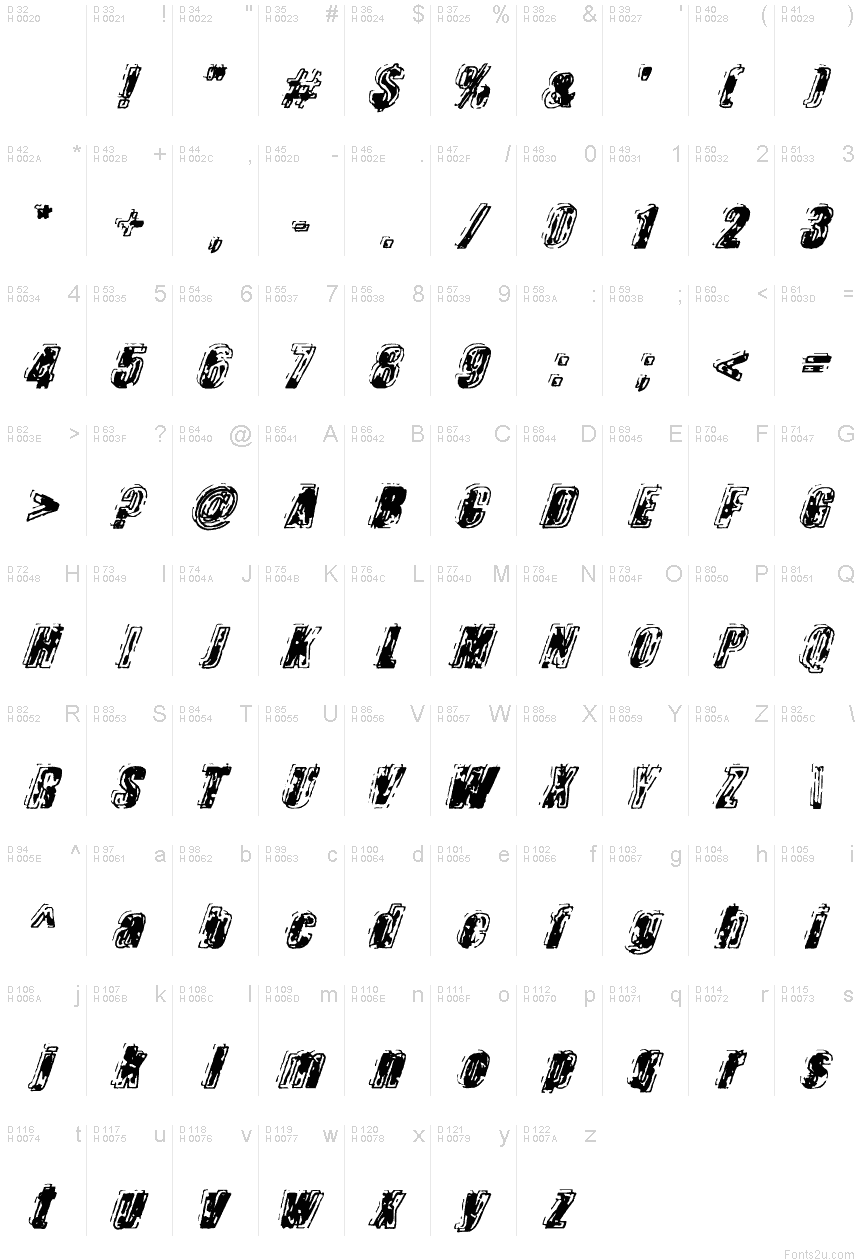
Zapped هو خط عرض (display font) مجاني مشوّه يتميز بمظهر حيوي ومصنوع يدوياً، وكأنه مستوحى من مؤثرات صوتية في القصص المصورة ومنشورات "البانك" المنسوخة ضوئياً. تبدو الحروف الكبيرة وكأنها خارج مكانها، مع أشكال ممتلئة وتراكبات خشنة وخطوط خارجية غير منتظمة، مما يجعل الحروف تبدو وكأنها ملطخة ونابضة وخارجة عن السيطرة قليلاً.
هذا الملمس المضطرب يجعل الخط المجاني مناسباً بشكل طبيعي للملصقات، والمجلات المستقلة (zines)، وأغلفة الألبومات، وعناوين أفلام الرعب، وتصاميم الألعاب (arcade)، والعلامات التجارية القصيرة، حيث يمكن للحروف أن تعمل كصورة بقدر ما تعمل كنص. يظهر الخط بأفضل حالاته في الجمل القصيرة - شعار، عنوان غلاف، بداية فصل، أو كلمة واحدة قوية - لأن أشكاله الممزقة وذات الصدى هي التي تقوم بمعظم العمل التعبيري.